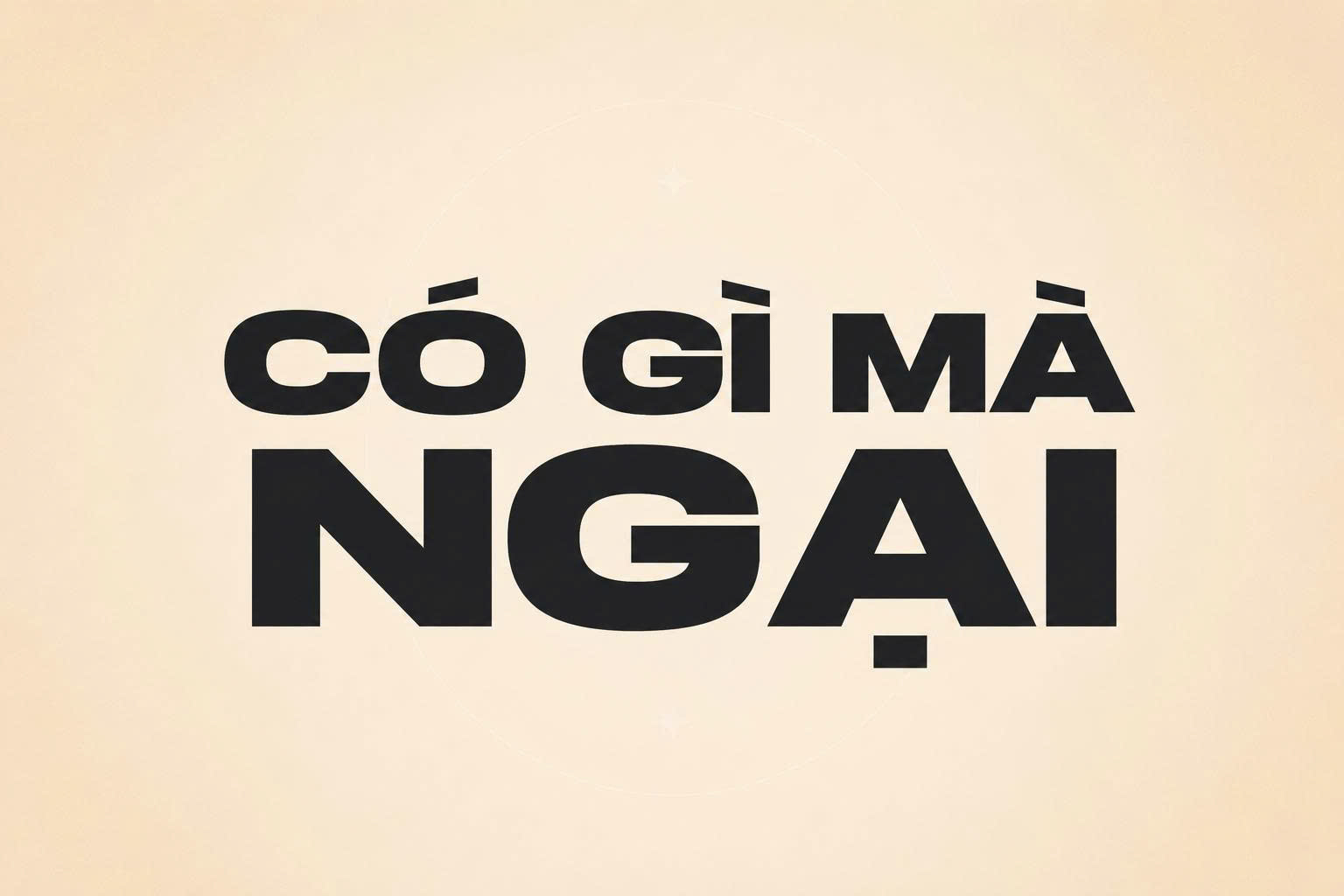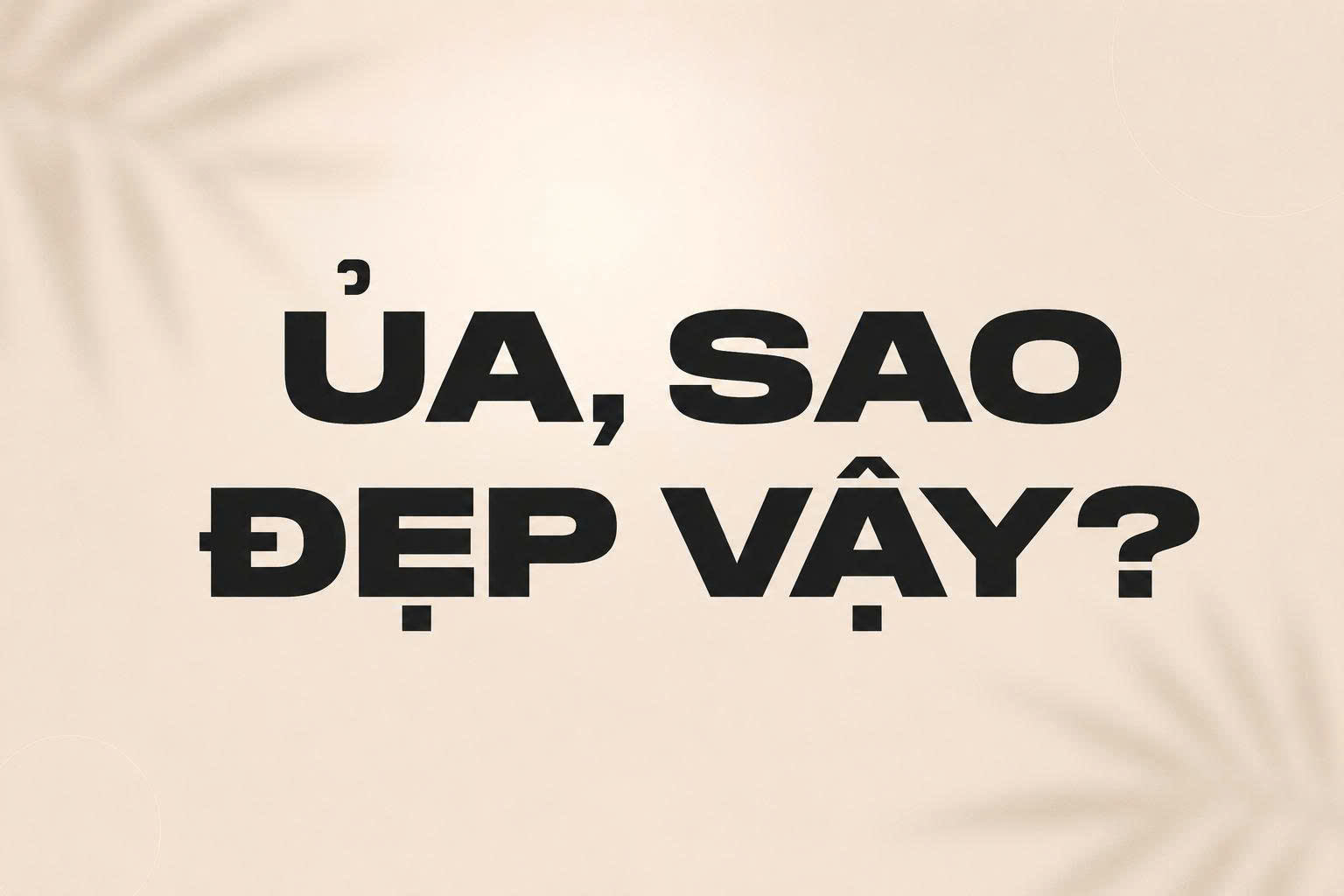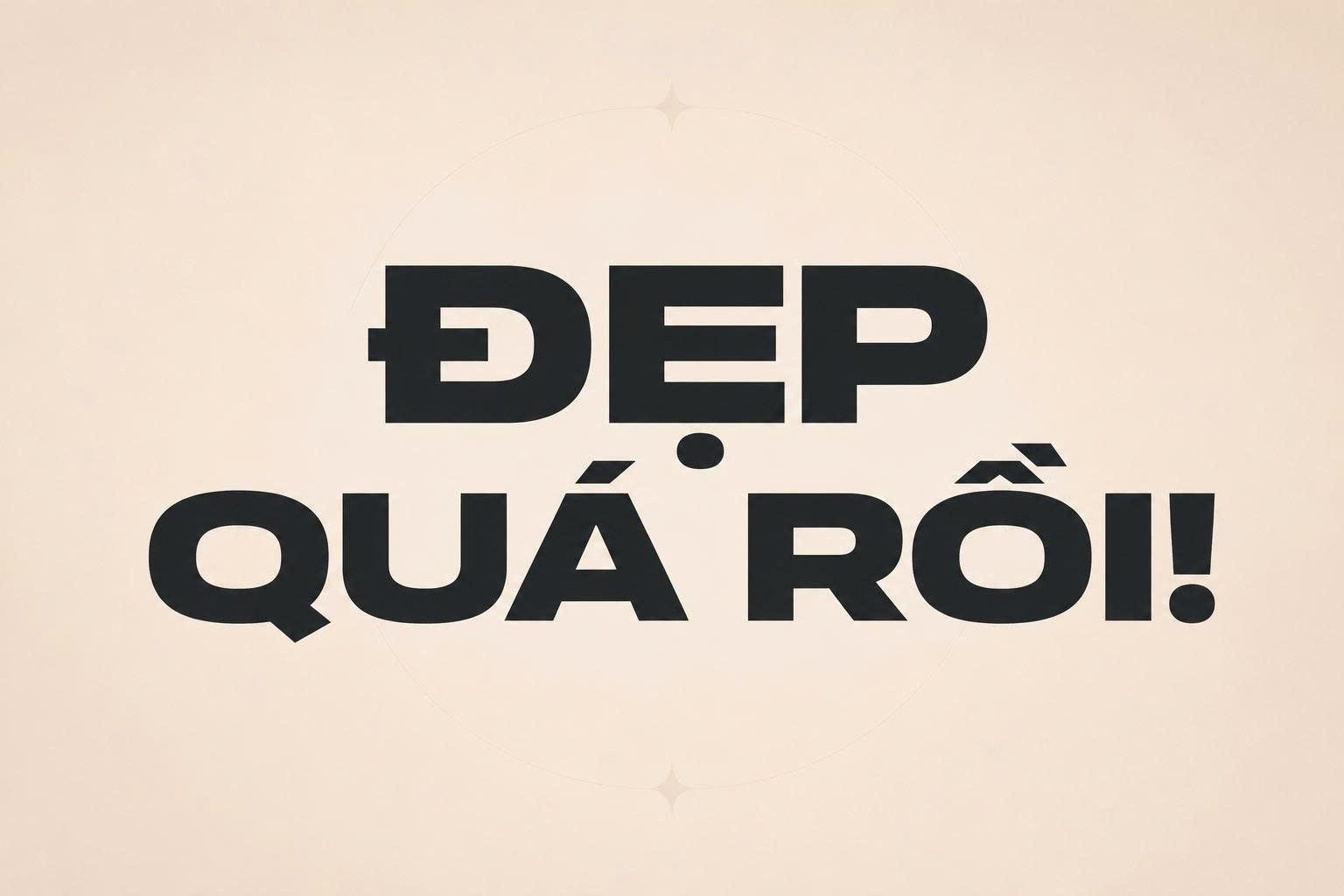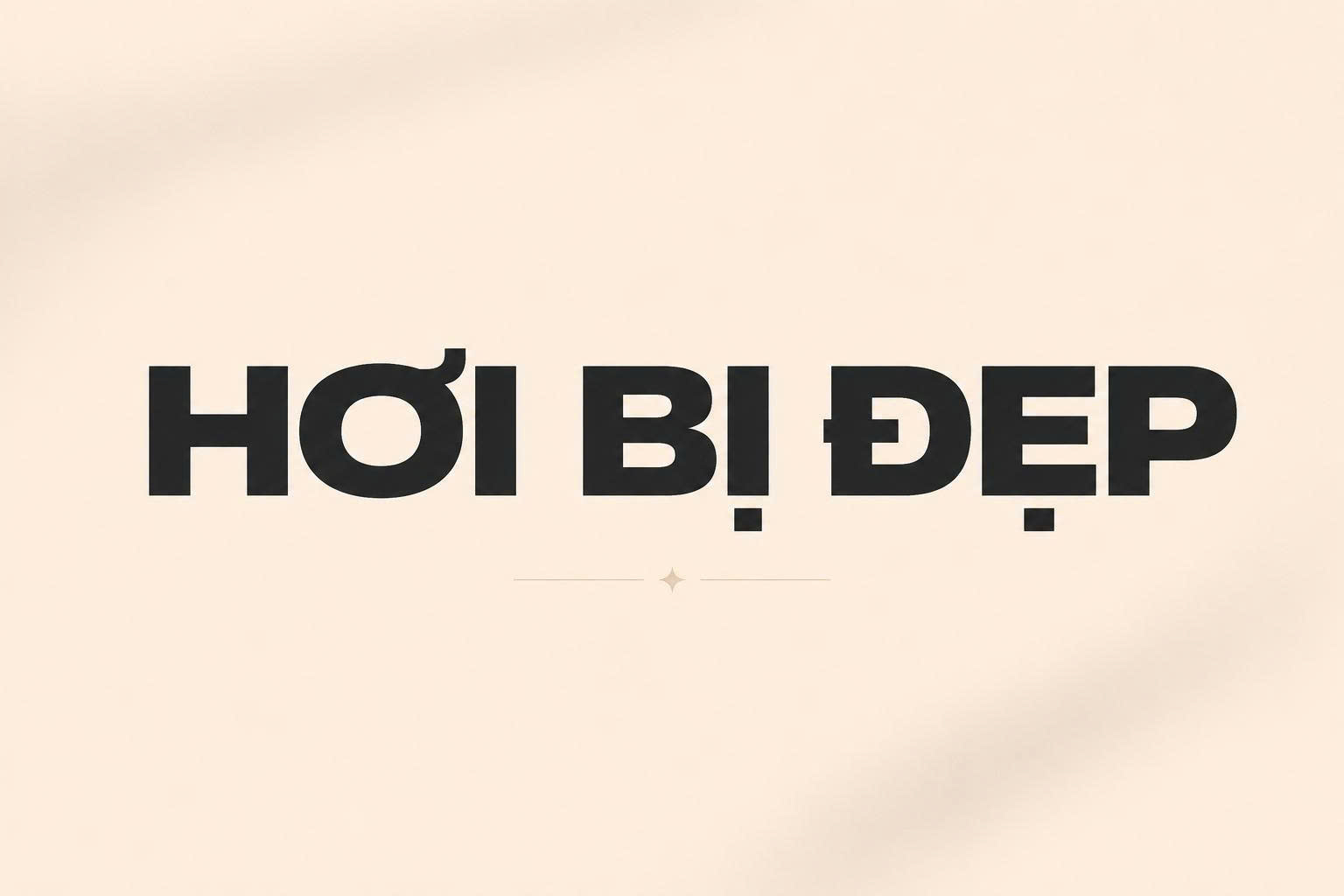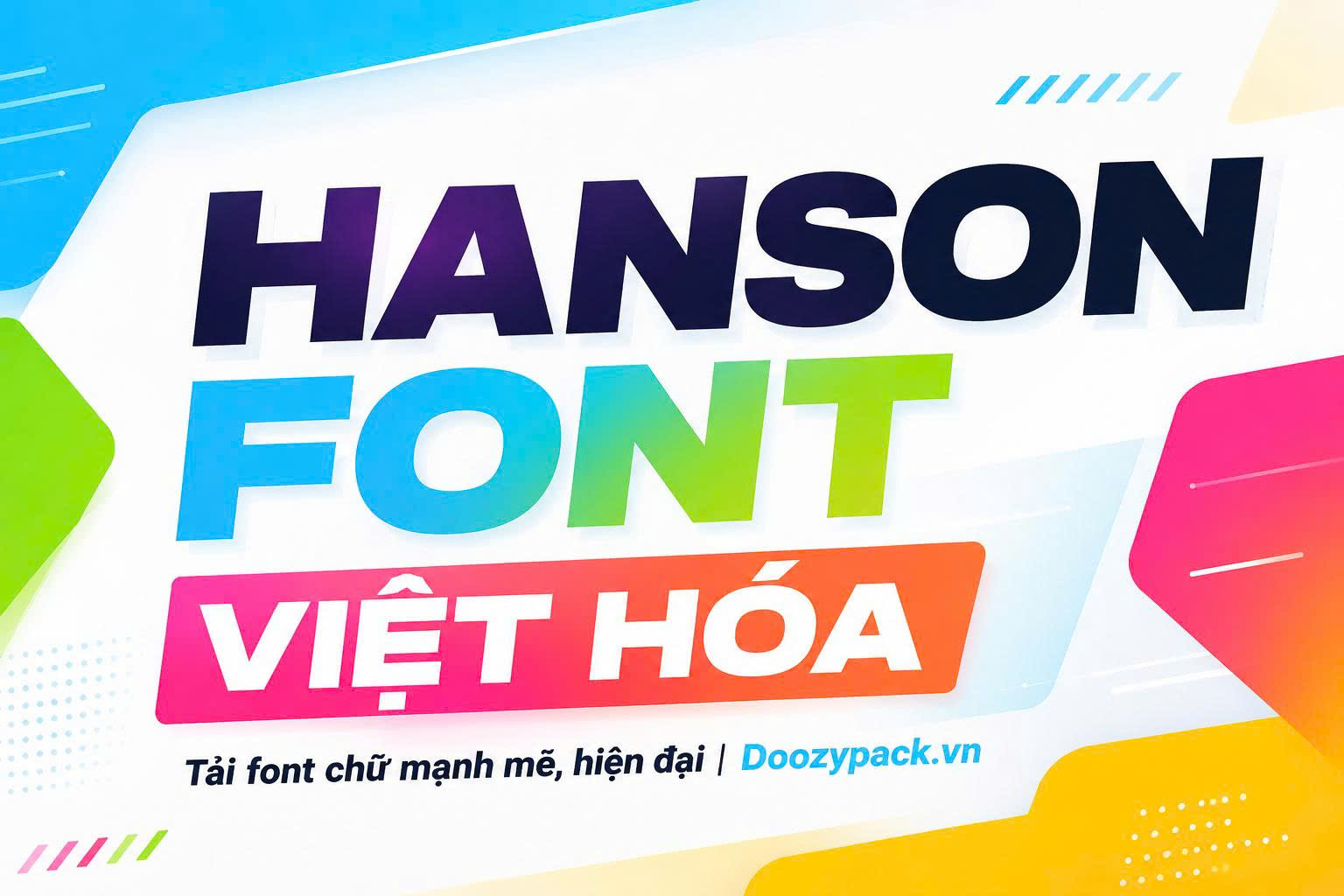
Hanson font Việt hóa là bộ phông chữ thuộc dòng Display Sans-serif nổi tiếng với cấu trúc nét dày (Bold), bản chữ rộng và phong cách vô cùng mạnh mẽ, hiện đại. Với thiết kế vững chãi và đầy uy lực, Hanson là lựa chọn lý tưởng cho các tiêu đề poster, logo thương hiệu và đặc biệt là bao bì sản phẩm công nghệ hoặc thể thao. Doozypack.vn cung cấp link tải font Hanson Việt hóa chuẩn, giúp bạn sở hữu bộ font Hanson tiếng Việt không lỗi dấu thanh để tạo nên những bản thiết kế ấn tượng và thu hút thị giác nhất.
Đặc điểm thiết kế đột phá của bộ font Hanson Việt hóa
Hanson không chỉ là một phông chữ đậm thông thường; nó mang trong mình tư duy thiết kế hiện đại, tối ưu cho các bề mặt hiển thị lớn.
Cấu trúc chữ Bold mạnh mẽ và bản rộng
Đặc trưng lớn nhất của font Hanson Việt hóa là độ dày nét chữ cực lớn kết hợp với cấu trúc chữ hơi mở rộng theo chiều ngang. Thiết kế này tạo nên một cảm giác uy tín, tin cậy và rất chắc chắn. Khi đặt Hanson làm tiêu đề trên một chiếc hộp giấy hoặc túi giấy, tên thương hiệu của bạn sẽ ngay lập tức trở thành tâm điểm của sự chú ý mà không cần đến các hiệu ứng đồ họa phức tạp.
Hệ thống dấu tiếng Việt được tinh chỉnh chỉn chu
Nỗi đau của các designer khi sử dụng font Hanson bản gốc là các bộ dấu tiếng Việt thường bị lỗi nhảy font hoặc không cân đối với thân chữ vốn rất dày. Phiên bản Việt hóa tại Doozypack.vn đã xử lý triệt để vấn đề này. Các dấu thanh được thiết kế với độ đậm tương đồng, vị trí đặt dấu được tính toán kỹ lưỡng để giữ nguyên nhịp điệu Typography mạnh mẽ của bộ font gốc.
Tại sao designer nên chọn font Hanson tiếng Việt cho thiết kế bao bì?
Trong ngành sản xuất bao bì tại Doozypack.vn, Hanson luôn nằm trong top các font chữ “High-impact” nhờ những ưu điểm vượt trội:
- Khả năng nhận diện cực cao: Nhờ nét chữ siêu đậm, Hanson hiển thị vô cùng rõ nét trên kệ hàng, giúp khách hàng dễ dàng nhận ra sản phẩm của bạn từ khoảng cách xa.
- Tính chuyên nghiệp và hiện đại: Hanson mang lại diện mạo “Startup” trẻ trung, rất phù hợp cho các ngành hàng thiết bị điện tử, phụ kiện ô tô hoặc thực phẩm chức năng cho vận động viên.
- Dễ dàng kết hợp kỹ thuật in ấn: Cấu trúc nét dày của Hanson là nền tảng hoàn hảo để ứng dụng các phương pháp gia công cao cấp như ép kim, dập nổi hoặc phủ UV định hình.
Lời khuyên từ xưởng in: Vì Hanson có nét chữ rất dày và chiếm diện tích lớn, khi in trên chất liệu giấy có bề mặt thấm mực mạnh như giấy Kraft, bạn nên tăng nhẹ khoảng cách giữa các chữ cái (Tracking) để tránh hiện tượng mực bị lan làm dính các nét chữ vào nhau.
03 Ứng dụng của font Hanson trong sản xuất bao bì tại Doozypack.vn
Sự vững chãi của Hanson mang lại hiệu quả thị giác đặc biệt trên các ấn phẩm thực tế do Doozypack.vn sản xuất:
- Bao bì linh kiện điện tử: In tên sản phẩm trên vỏ hộp chuột gaming, bàn phím hoặc tai nghe tạo cảm giác hiện đại và đẳng cấp.
- Túi giấy doanh nghiệp: Tên công ty in bằng font Hanson trên túi giấy Ivory cán màng mờ mang lại diện mạo vô cùng chuyên nghiệp và vững chắc.
- Tem nhãn sản phẩm: Phù hợp cho các tem nhãn decal dán trên hộp đựng dụng cụ cầm tay hoặc thực phẩm đóng gói phong cách công nghiệp.
03 Lưu ý kỹ thuật khi in ấn font chữ nét đậm như Hanson
Việc sản xuất bao bì sử dụng phông chữ siêu đậm đòi hỏi designer cần lưu ý một số vấn đề kỹ thuật tại xưởng in chuyên nghiệp:
- Kiểm soát độ phủ mực: Nét chữ dày tiêu tốn nhiều mực hơn. Để đảm bảo màu sắc đồng đều, Doozypack.vn khuyên bạn nên sử dụng hệ màu CMYK và đặt màu đen cho văn bản ở thông số K=100 thay vì đen tổng hợp để tránh hiện tượng nhòe màu.
- Gia công ép kim và dập nổi: Nhờ bề mặt chữ lớn, Hanson cực kỳ phù hợp cho kỹ thuật ép kim vàng hoặc dập nổi 3D. Những phương pháp này sẽ làm nổi bật sự uy lực của font chữ trên nắp hộp quà tặng cao cấp.